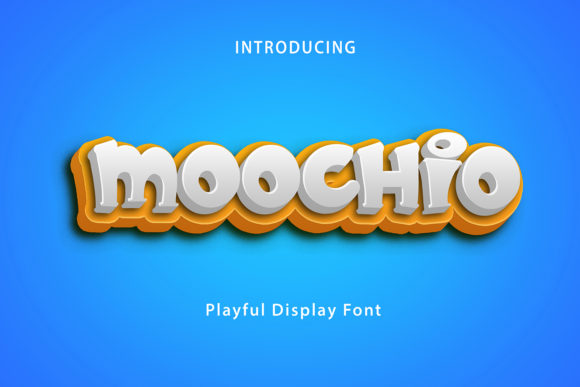
Creativefabrica Moochio Font
[Creativefabrica] Moochio Font
Мучио - милый, игривый шрифт.
Причудливый и немного причудливый, этот шрифт скрасит каждое ваше оформление.
Добавьте его уверенно в свои проекты, и вам понравится результат.